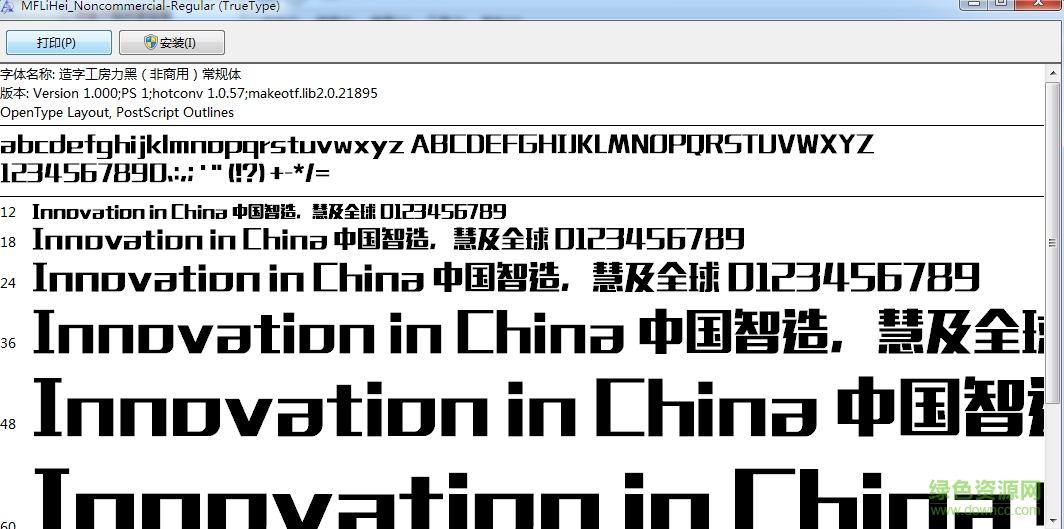
mflihei 什么字體?mfliheino字體即造字工房力黑常規(guī)體,是非商業(yè)使用的黑體字體,整體簡單大氣,自帶加黑加粗設(shè)計(jì),讓文字更加顯眼,喜歡的朋友記得來綠色資源網(wǎng)體驗(yàn)哦!
本字體為簡體字庫,采用OpenType/CID 格式, Adobe-GB1-5編碼?;谥腥A人民共和國GB2312-80字符集標(biāo)準(zhǔn), 另按需添加了 103 個(gè)漢字。共收容字?jǐn)?shù) 6866 CJK 漢字,ASCII常用字符100個(gè)。
造字工房力黑體筆畫厚重,強(qiáng)有力度,字形蒼勁,筆勢(shì)頓挫有序,整體形態(tài)給人以明朗、堅(jiān)實(shí)之感,傳達(dá)給人果敢和進(jìn)取的態(tài)度。直角與圓角的搭配使字形整體特征剛?cè)岵?jì),極具現(xiàn)代感。具有較大范圍的應(yīng)用空間。尤其在促銷或競技視覺環(huán)境中有良好的表現(xiàn)力!